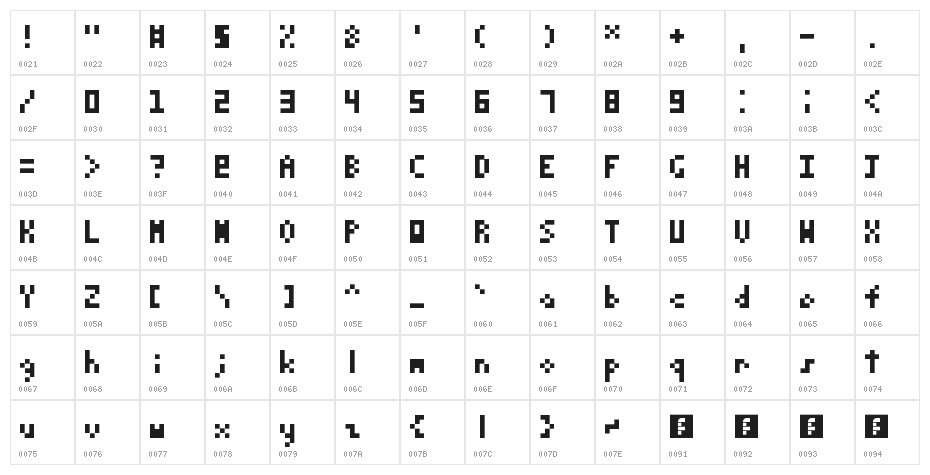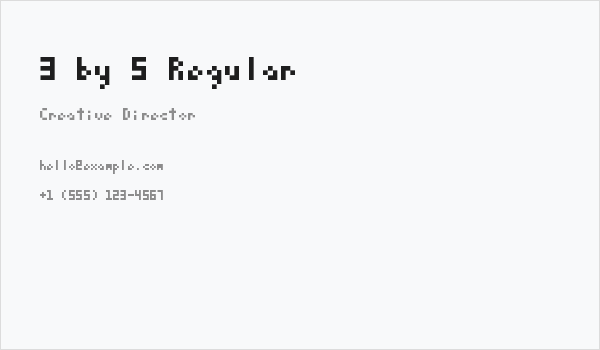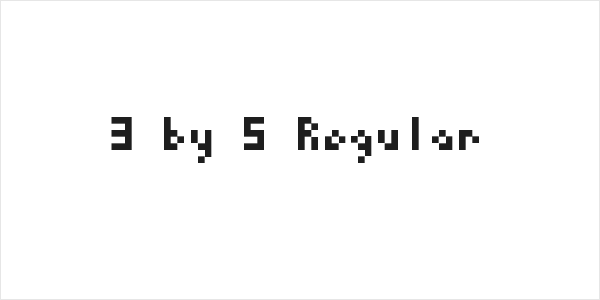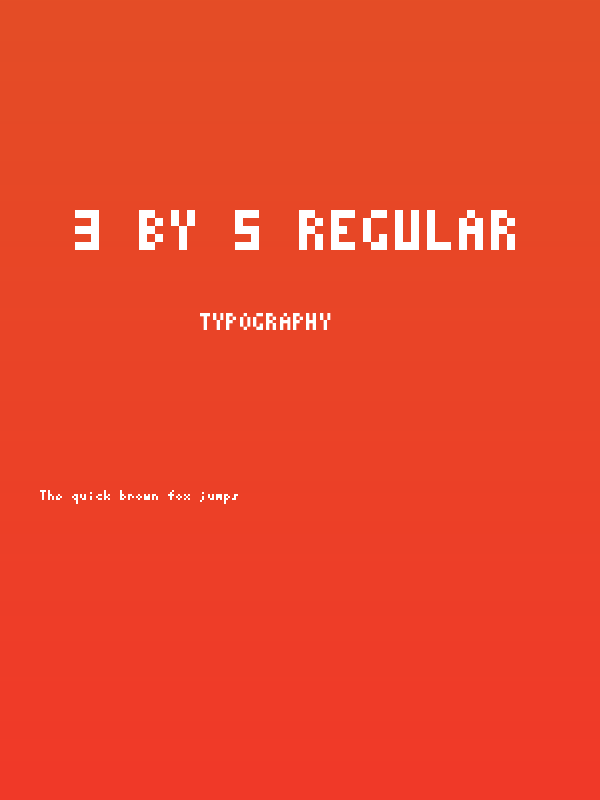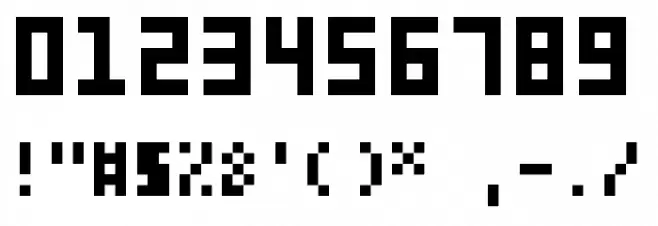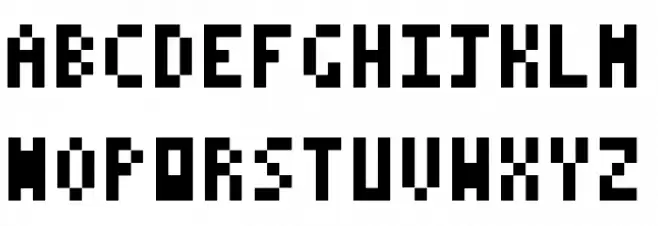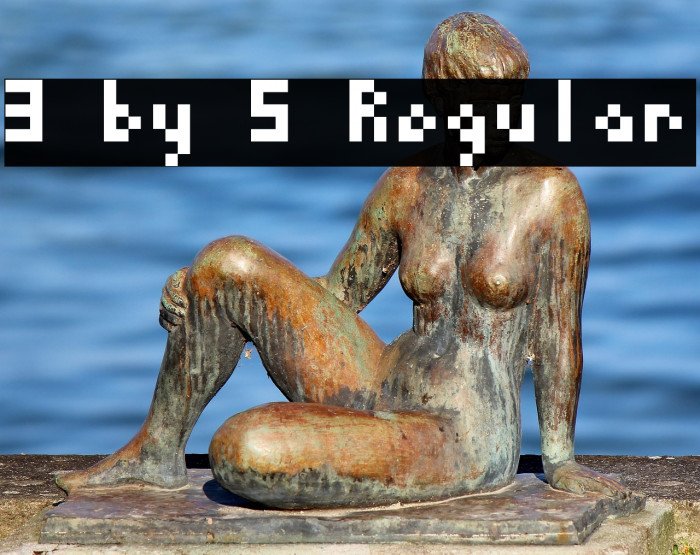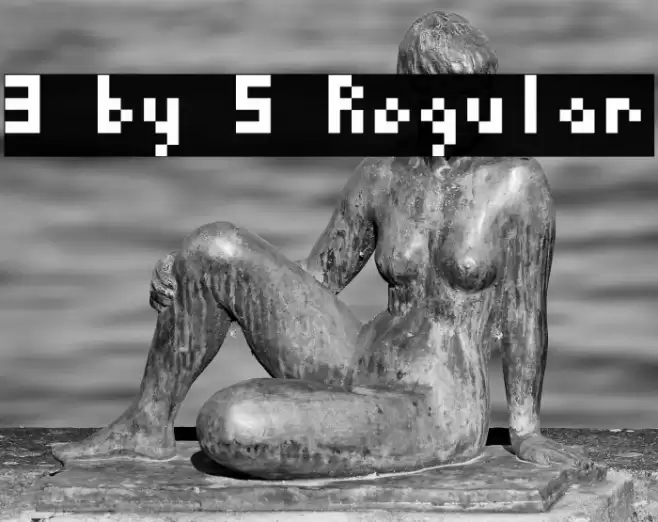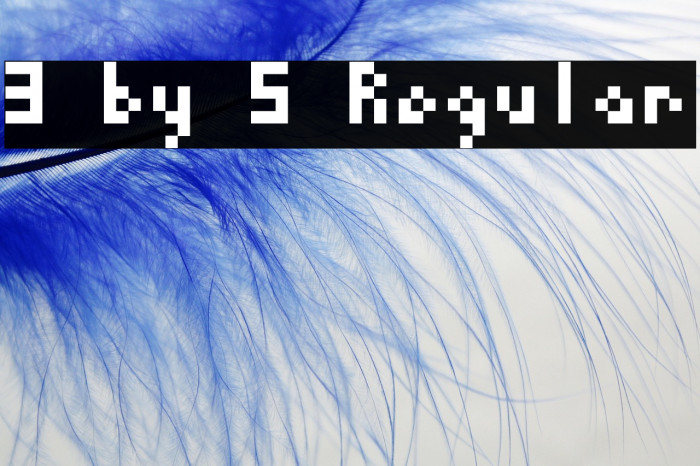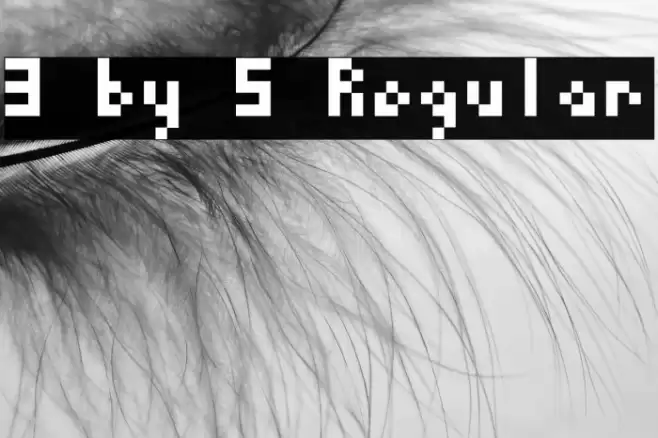
3 by 5 Regular Font
| الاسم | 3 by 5 Regular |
| عائلة الخط | 3 by 5 |
| Style | D-by-5 |
| الفئات | Regular |
| النمط العام | Vintage |
| حالة الاستخدام | Logos, Headlines, Digital Art |
| مشاريع مقترحة | Ideal for retro video game designs, digital art projects, tech-themed posters, and any creative work that seeks to evoke a sense of nostalgia for early digital aesthetics. |